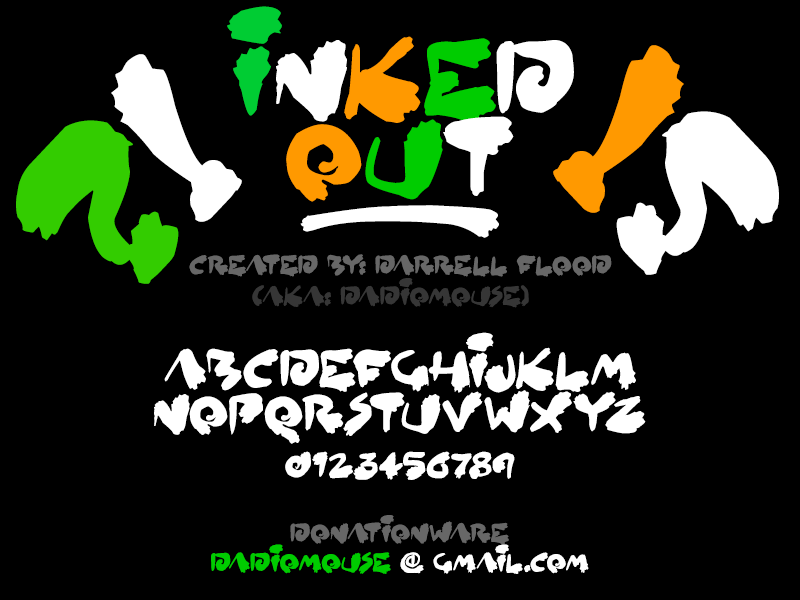
A Inked Out Brush Font é uma criação do designer Darrell Flood disponível gratuitamente para uso pessoal. Embora a fonte esteja disponível de graça, qualquer contribuição financeira é sempre apreciada – seja para fins comerciais ou não, um valor mínimo sugerido é de US$10 por pagamento. Esta fonte é ideal para quem busca uma adição elegante e versátil ao seu design, oferecendo uma variedade de opções de estilo na escrita cursiva. Para usuários com necessidades comerciais, a Inked Out Brush Font requer um mínimo de contribuição financeira. Este valor não apenas reconhece o trabalho meticuloso da fonte e seus criadores, mas também apóia projetos futuros que podem tornar esta fonte ainda mais versátil para designers e artistas gráficos. Essa fonte é perfeitamente adequada para quem deseja adicionar um toque único a qualquer projeto visual, seja em designs de marca ou para trabalhos publicitários.